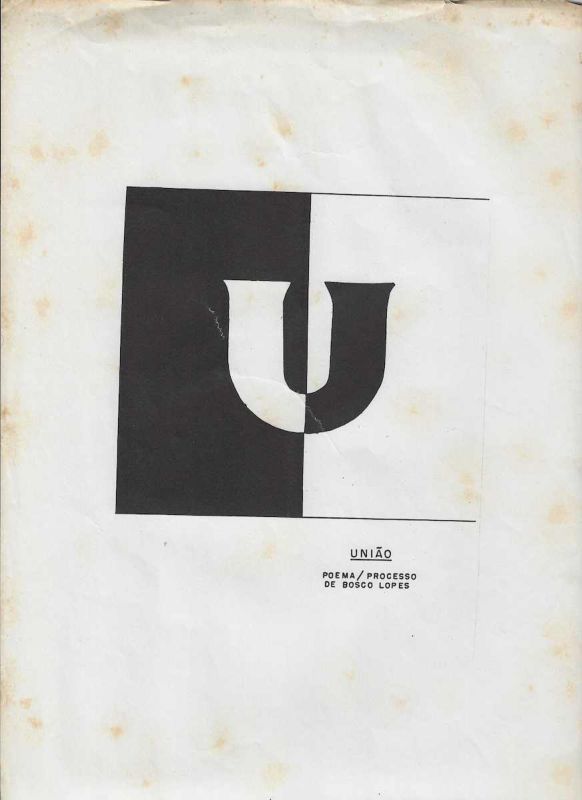
União é um poema processo de Bosco Lopes construído a partir da síntese entre forma gráfica, tipografia e conceito visual.
União é um poema processo de Bosco Lopes construído a partir da síntese entre forma gráfica, tipografia e conceito visual. A composição apresenta uma estrutura baseada na oposição entre preto e branco, utilizando o contraste como elemento gerador de significado. No centro da obra, a letra U surge simultaneamente como signo verbal e forma visual, articulando ideias de complementaridade, integração e convergência. A solução gráfica reduz os elementos ao essencial, característica presente em importantes experiências do movimento Poema Processo, onde a imagem substitui a narrativa verbal tradicional e passa a atuar como linguagem autônoma. A obra demonstra o interesse de Bosco Lopes pela economia formal e pela comunicação direta, transformando uma estrutura tipográfica simples em reflexão visual sobre encontro, unidade e relação entre opostos.Texto de Observação (Português)Impresso de Bosco Lopes vinculado às pesquisas do movimento Poema Processo. A composição utiliza contraste cromático, geometria e tipografia para construir uma leitura visual baseada na ideia de união entre elementos complementares. Exemplar de significativa síntese formal e conceitual.Salsa Program Text (English)Union is a process poem by Bosco Lopes built through the synthesis of graphic form, typography and visual concept. The composition is structured around the opposition between black and white, using contrast as the primary generator of meaning. At the center of the work, the letter U appears simultaneously as a verbal sign and a visual form, articulating ideas of complementarity, integration and convergence. The graphic solution reduces the elements to their essentials, a characteristic found in important experiments of the Poema Processo movement, where the image replaces traditional verbal narrative and operates as an autonomous language. The work demonstrates Bosco Lopes's interest in formal economy and direct communication, transforming a simple typographic structure into a visual reflection on encounter, unity and the relationship between opposites.Observation Text (English)Printed work by Bosco Lopes associated with the investigations of the Poema Processo movement. The composition employs chromatic contrast, geometry and typography to create a visual reading centered on the idea of union between complementary elements. An example of remarkable formal and conceptual synthesis.
Impresso de Bosco Lopes vinculado às pesquisas do movimento Poema Processo. A composição utiliza contraste cromático, geometria e tipografia para construir uma leitura visual baseada na ideia de união entre elementos complementares. Exemplar de significativa síntese formal e conceitual.Printed work by Bosco Lopes associated with the investigations of the Poema Processo movement. The composition employs chromatic contrast, geometry and typography to create a visual reading centered on the idea of union between complementary elements. An example of remarkable formal and conceptual synthesis.
Union is a process poem by Bosco Lopes built through the synthesis of graphic form, typography and visual concept